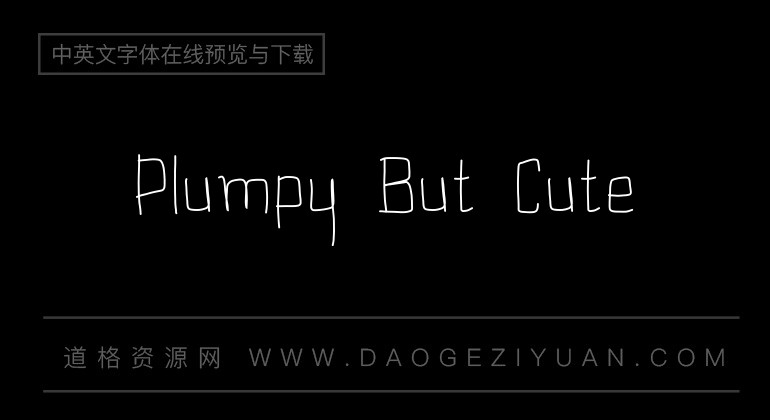
Plumpy But Cute
? Plumpy But Cute 是一款个性十足的手写字体,它具有柔和的笔画,拥有浓浓的情感,给人一种温馨、可爱的感觉。它的字形比较宽松,每个字母都有自己的特点,形状可爱,给人一种活泼的感觉。这款字体适合用于手写艺术、小清新的卡片、海报、日记等,可以给大家带来温馨的感受。
Plumpy But Cute是一款非常不错的手写艺术字体,具有很好的视觉感,适合于文化类的宣传设计、商业类品牌的广告和产品包装设计以及个性化文字排版等较多场景。
Plumpy But Cute字符映射图